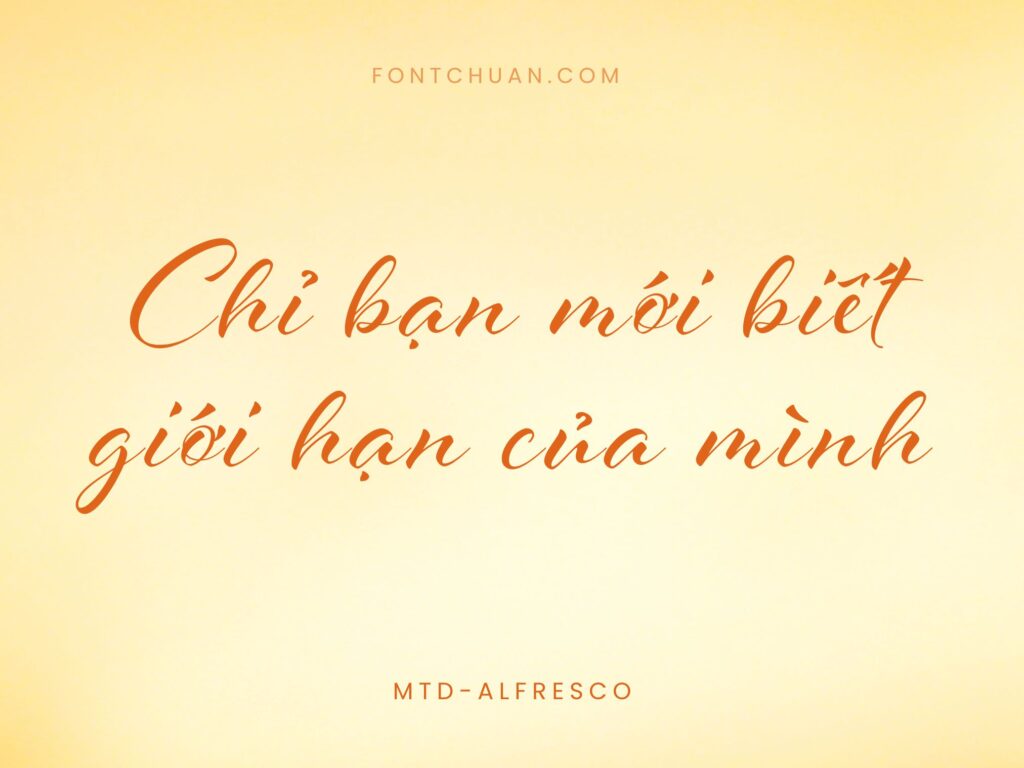
Font Al Fresco là một kiểu chữ viết tay tự do, được thiết kế bởi Laura Worthington và phát hành vào năm 2013. Lấy cảm hứng từ phong cách sống thoải mái và tự nhiên, Al Fresco mang đến cảm giác thân thiện và ấm áp cho các thiết kế.
Phiên bản Al Fresco đã được Việt hóa bởi Mộc Hạ, hỗ trợ đầy đủ tiếng Việt cùng hơn 18 ngôn ngữ khác như Anh, Pháp, Tây Ban Nha, Đức, Ý và Bồ Đào Nha, mở rộng khả năng ứng dụng trong thiết kế đa ngôn ngữ. Font này đã được thành viên Font Chuẩn sưu tầm và chia sẻ, đáp ứng nhu cầu của cộng đồng thiết kế. Với thiết kế bao gồm các ký tự viết tay mềm mại và tự nhiên, Al Fresco phù hợp cho các ứng dụng như thiết kế logo, thiệp mời, bao bì sản phẩm và các ấn phẩm quảng cáo. Các ngành nghề như quảng cáo, giáo dục, công nghệ và ẩm thực có thể tận dụng font này để tạo ra thiết kế ấn tượng và thu hút.